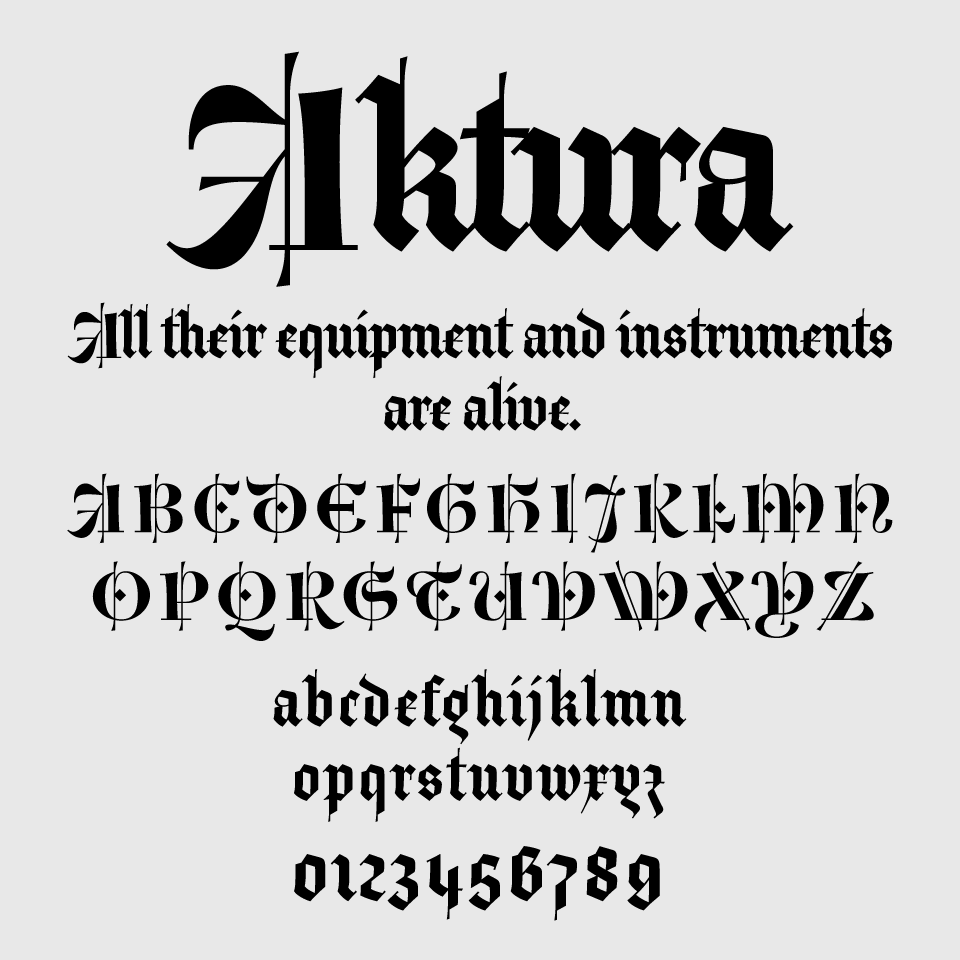
Akturaフォントは、中世の写本やグリモワールを連想させる、重厚で荘厳なブラックレター体です。
鋭くとがったエレメントや、大胆に入った縦線が特徴的で、ファンタジーな雰囲気や神秘性なストーリー性を感じるデザインです。
細かな装飾が細部まで行き届いており、文字というよりは装飾的なモチーフのように見える場面もあります。歴史や伝統を想起させるため、映画のタイトルロゴやコンセプチュアルなイベントのビジュアルなど、非日常を演出したい場面でぴったりなフォントです。